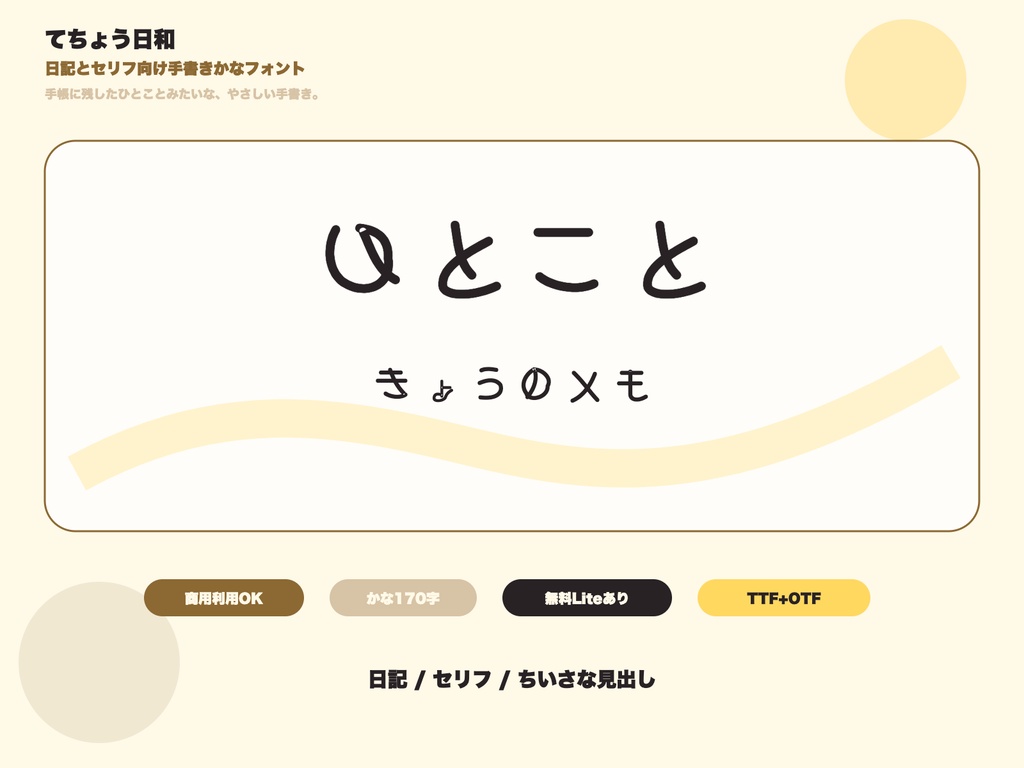
手帳に残したひとことみたいな、やさしい手書き。
落ち着いた手帳の手書き。少しだけ人の気配があって、子どもっぽくなりすぎない——そんな塩梅のかなフォントです。日記風の引用、キャラクターのセリフ、歌詞、やわらかい告知カードに。読ませたい文章にそっと体温をのせられます。
【想定用途】日記風の引用/キャラのセリフ/歌詞カード/やわらかい告知